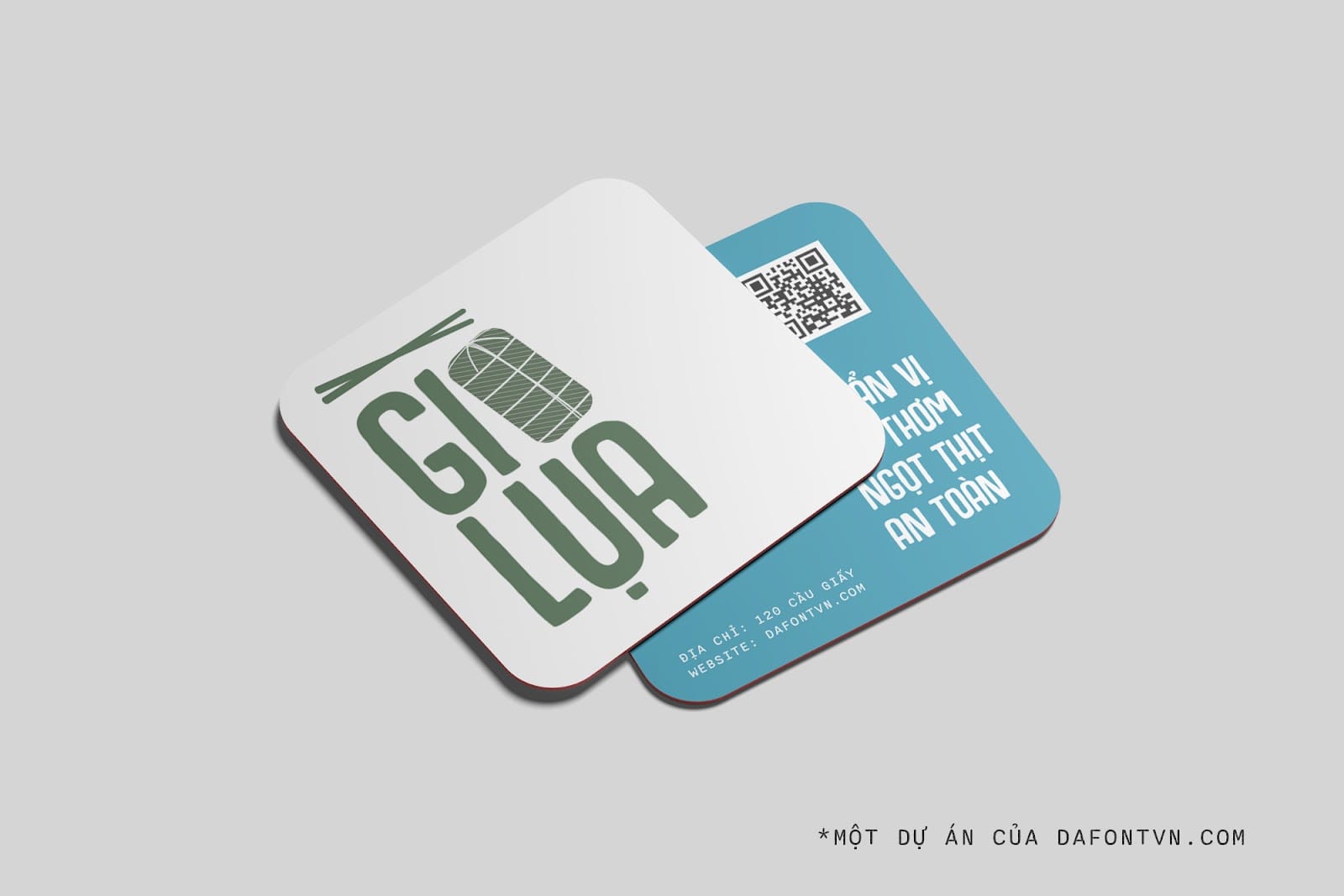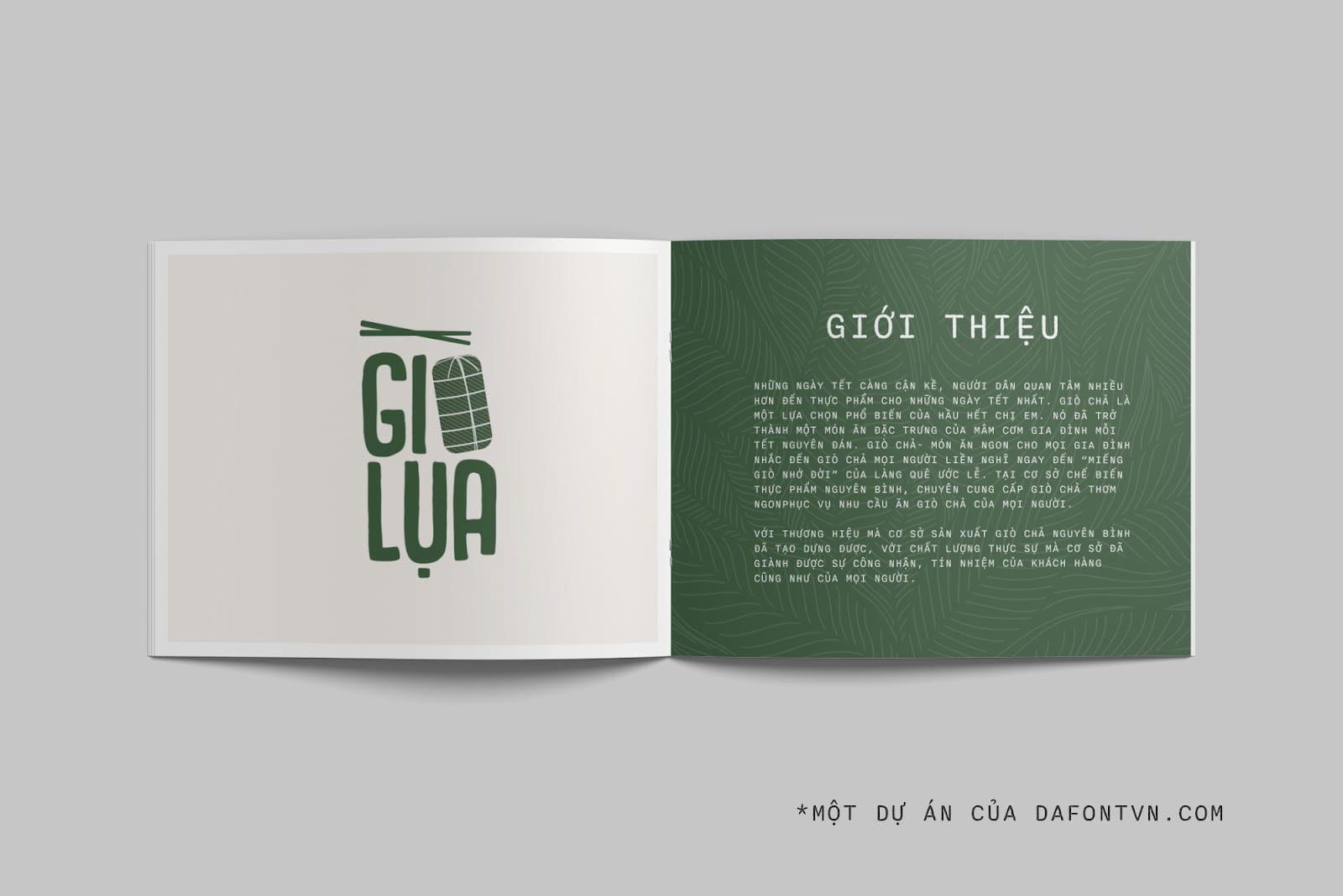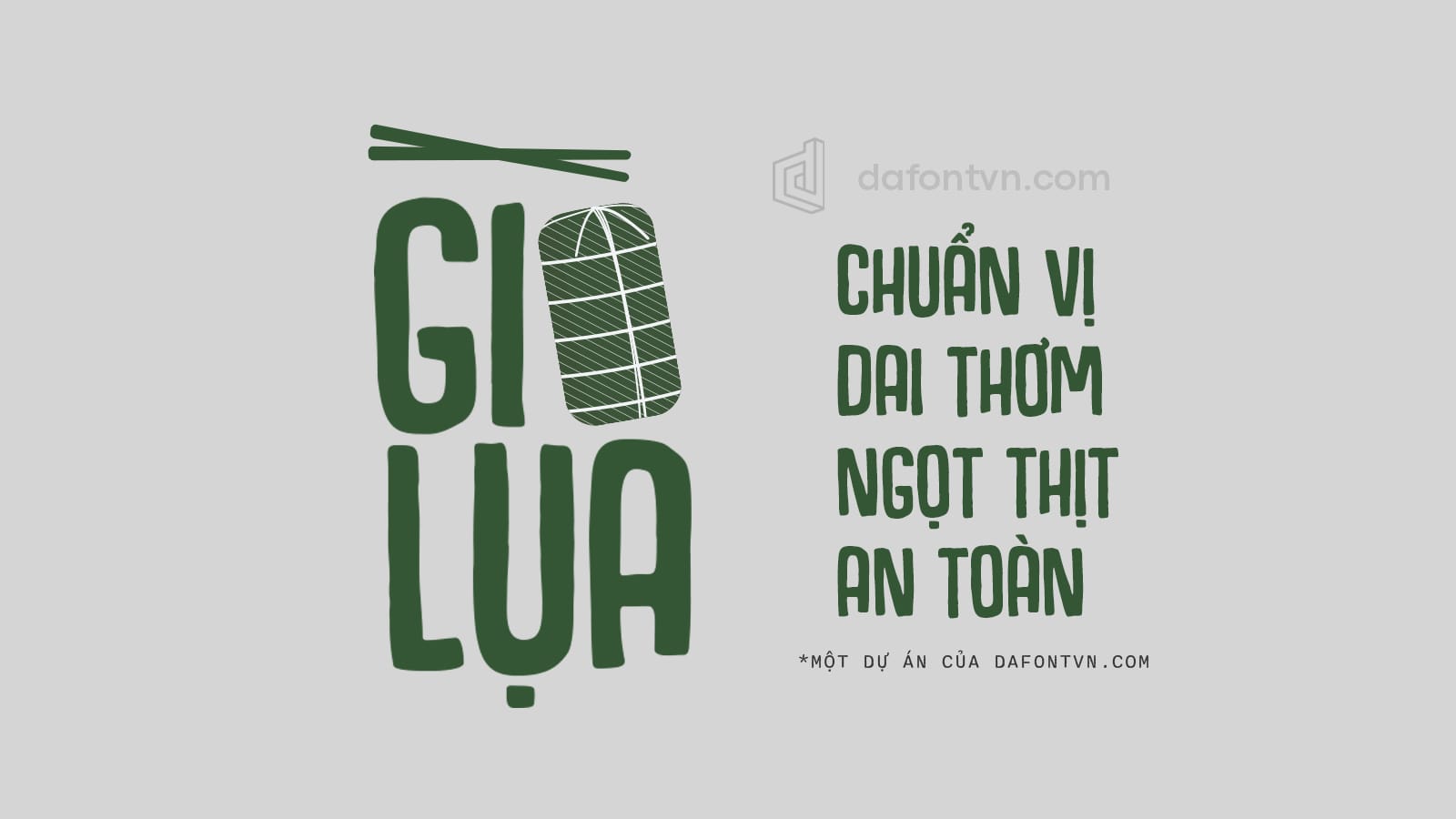
Hogfish Font Việt Hóa là một trong những font mà mình khá thích, mình đã sử dụng font này cho dự án thiết kế mới đây, dù font chữ đa ra đời cách đây khá lâu nhưng font này vẫn phù hợp với rất nhiều thiết kế khác nhau như xây dựng thương hiệu, tạp chí, bìa sách, tiêu đề… Hôm nay mình sẽ chia sẻ lại font này đã việt hóa đầy đủ, kerning và chỉnh sửa lại khá nhiều so với font gốc.